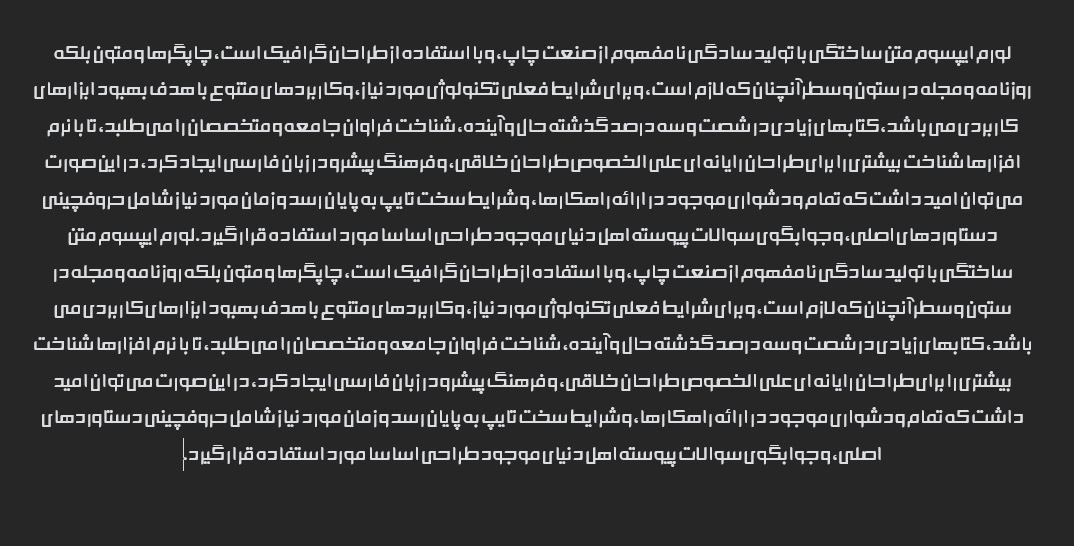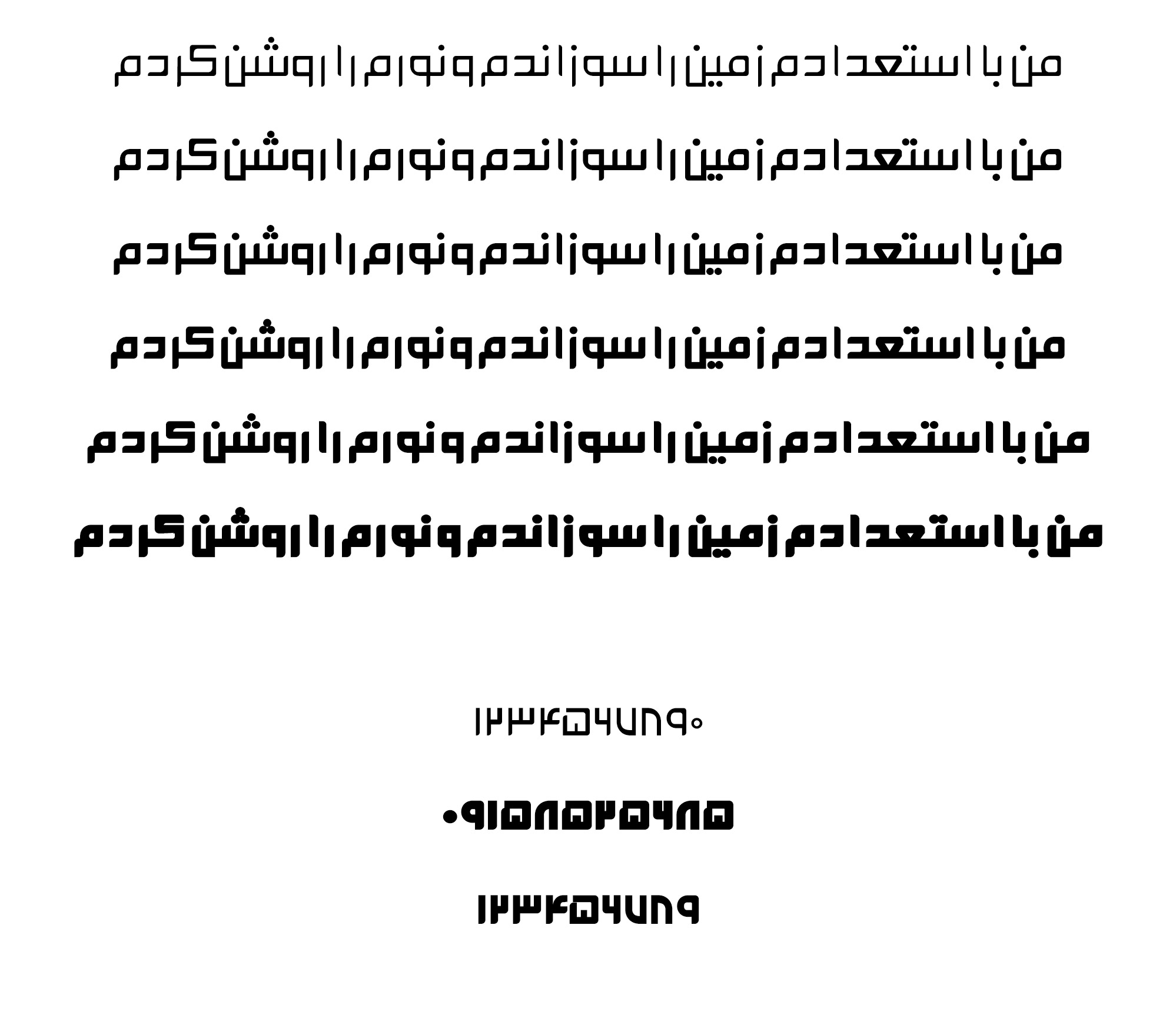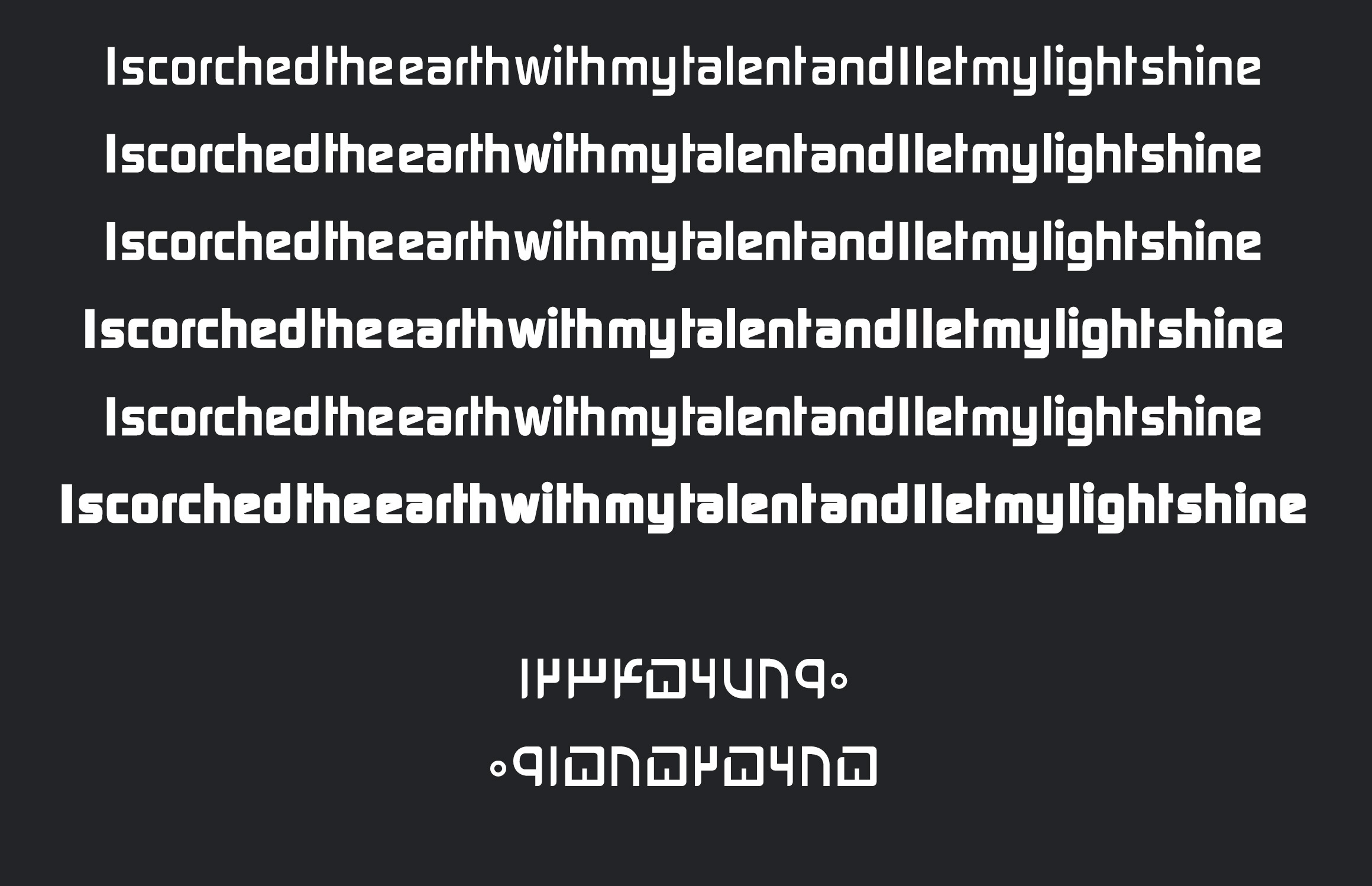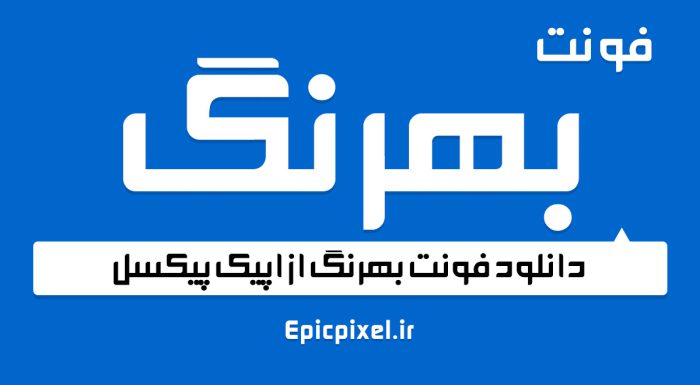
6 فونت بهرنگ فارسی
فونت فارسی بهرنگ، با طراحی خاص و منحصربه فردش، گزینه ای ایده آل برای کسانی است که به دنبال تایپوگرافی مدرن و چشم نواز هستند. این فونت که الهام گرفته از لوگوتایپ «آخرین خبر» است، به خوبی می تواند در طراحی لوگو، عناوین و پوسترهای تبلیغاتی شما بدرخشد.
یکی از ویژگی های برجسته بهرنگ، قابلیت مانور بالای آن در طراحی لوگوتایپ است؛ به این معنی که به راحتی می توان با آن لوگوهای خلاقانه و به یادماندنی خلق کرد. ساختار این فونت به گونه ای است که هم در فضاهای رسمی و هم در طرح های غیررسمی قابل استفاده است. بهرنگ در سه وزن مختلف (که در برخی نسخه ها ارائه می شود) عرضه شده تا دست شما را در انتخاب ضخامت مناسب برای متن باز بگذارد.
با این حال، باید به این نکته هم اشاره کرد که بهرنگ، به دلیل طراحی خاصش، شاید برای متن های طولانی و کتاب ها چندان مناسب نباشد و بیشتر برای عناوین کوتاه و جلوه های بصری قوی توصیه می شود. اگر به دنبال فونتی هستید که هم زیبایی بصری داشته باشد و هم در طراحی لوگو و عناوین به شما کمک کند، فونت بهرنگ می تواند انتخاب بسیار خوبی باشد. این فونت با فرمت استاندارد TTF ارائه می شود و در اکثر نرم افزارهای گرافیکی قابل استفاده است.